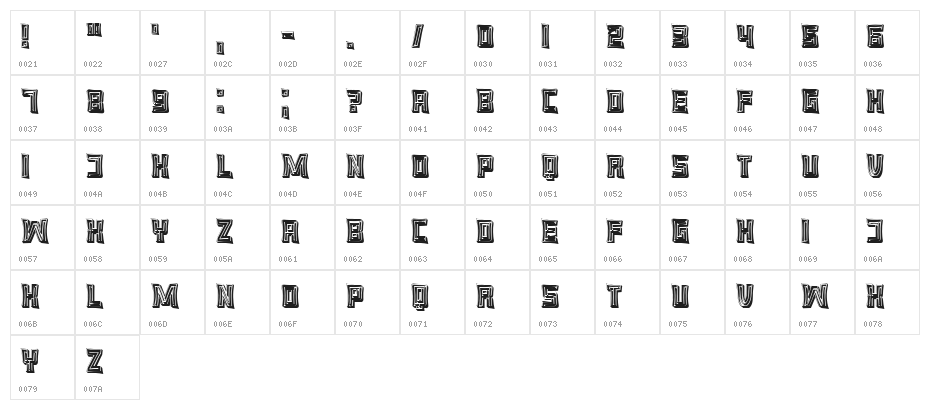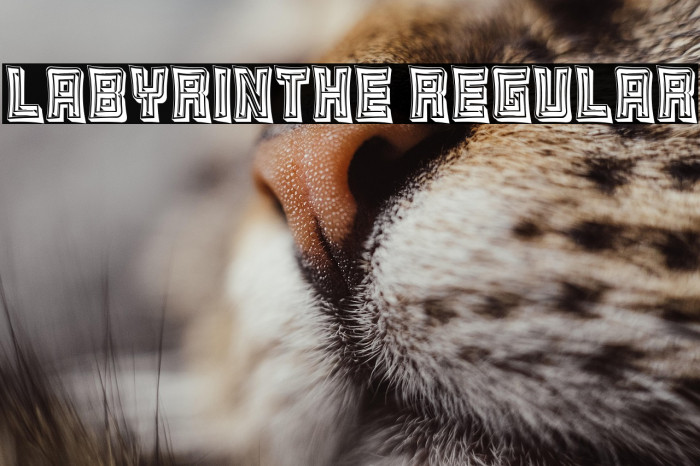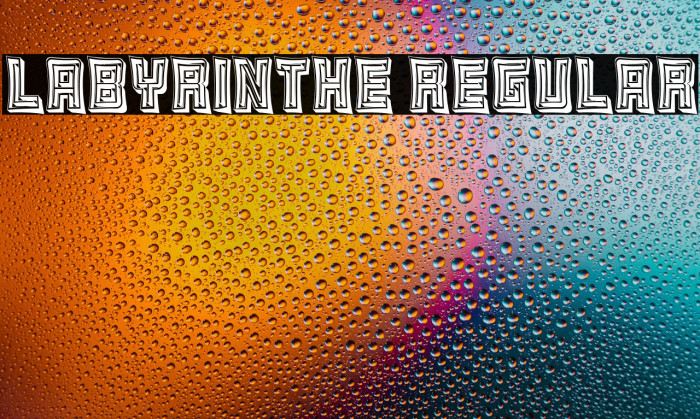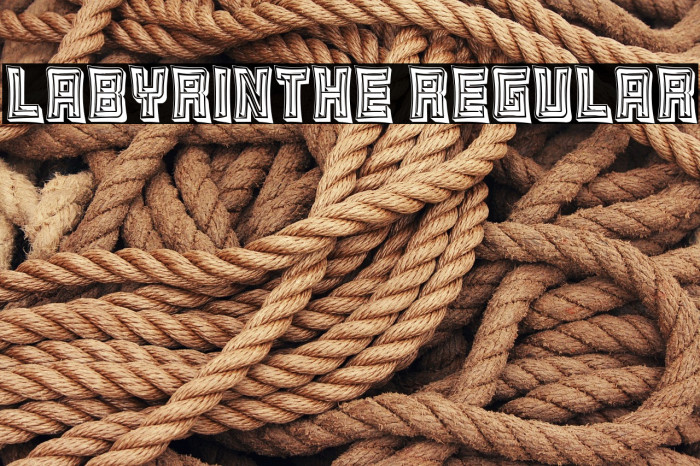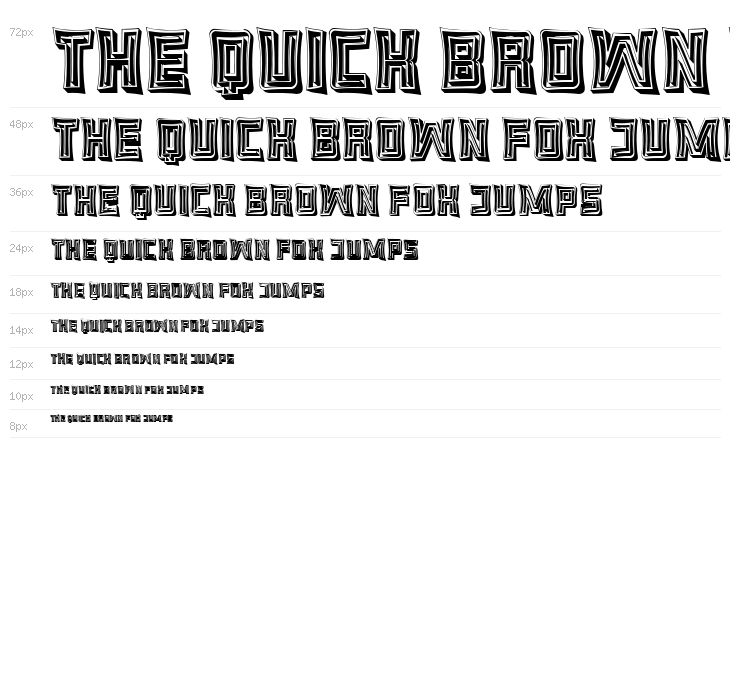
Labyrinthe Regular Font
✎ Decorative
| Proyectos propuestos | Ideal for posters, logos, video game titles, and any project needing a bold, eye-catching typeface. |